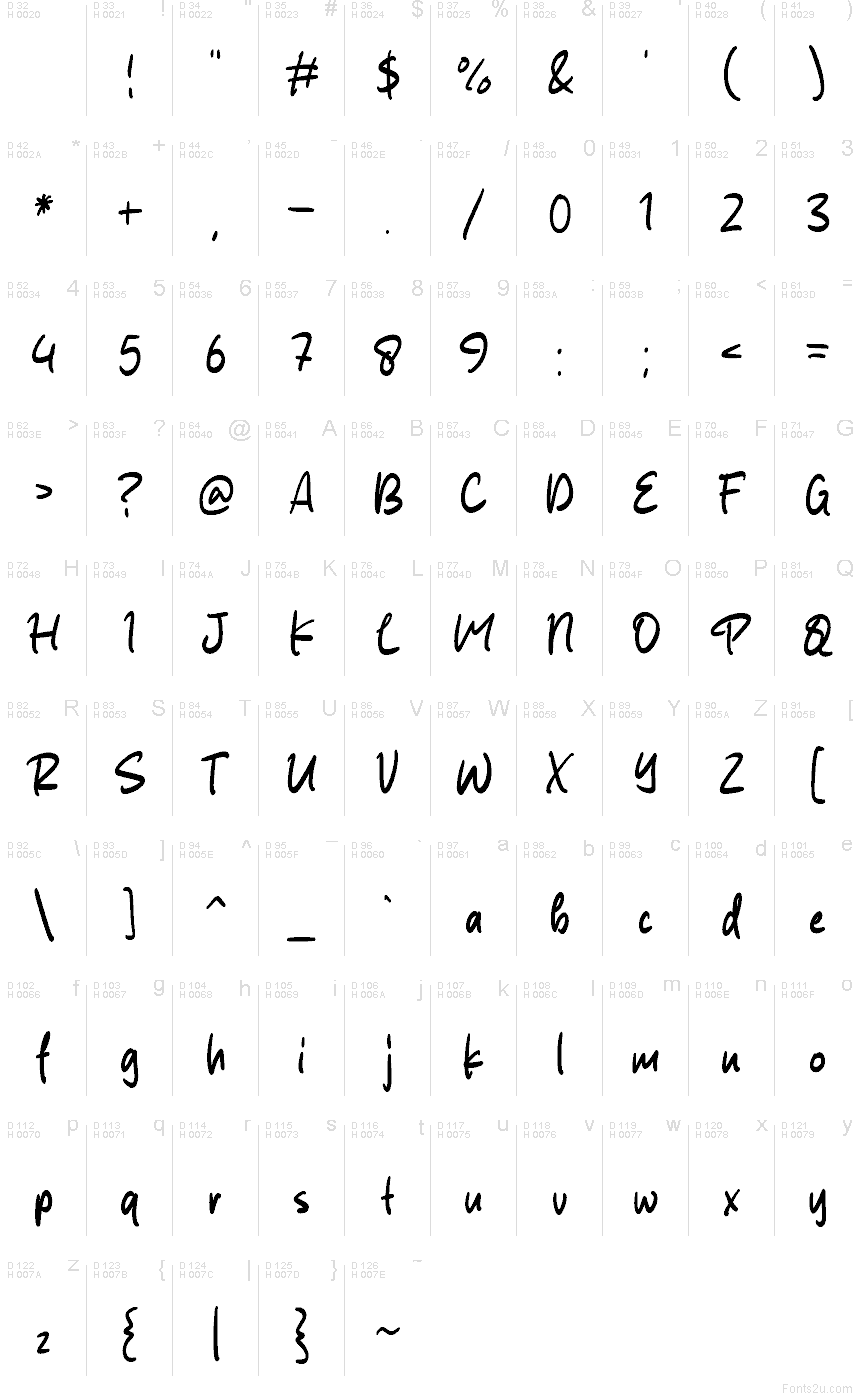
Rumble Notes
Rumble Notes di MJType è un font scritto a mano in stile pennello, gratuito, caratterizzato da un ritmo veloce e disinvolto con un tocco rétro che ricorda i pennarelli. Le lettere oscillano tra curve ampie e tondeggianti e giunzioni strette, dando al tratto un aspetto spontaneo e umano, lontano da una precisione meccanica. Le aste alte e le curve morbide lo rendono davvero vivace.
È ideale per titoli di locandine, branding di caffetterie, packaging, copertine di taccuini e grafiche per i social media dove serve un tocco calligrafico con un certo peso. Essendo un font gratuito, è perfetto anche per citazioni brevi, volantini di eventi e bozze di loghi audaci, specialmente quando si cerca un lettering che sembri scritto con un gesto sicuro e fluido, piuttosto che disegnato con cura.